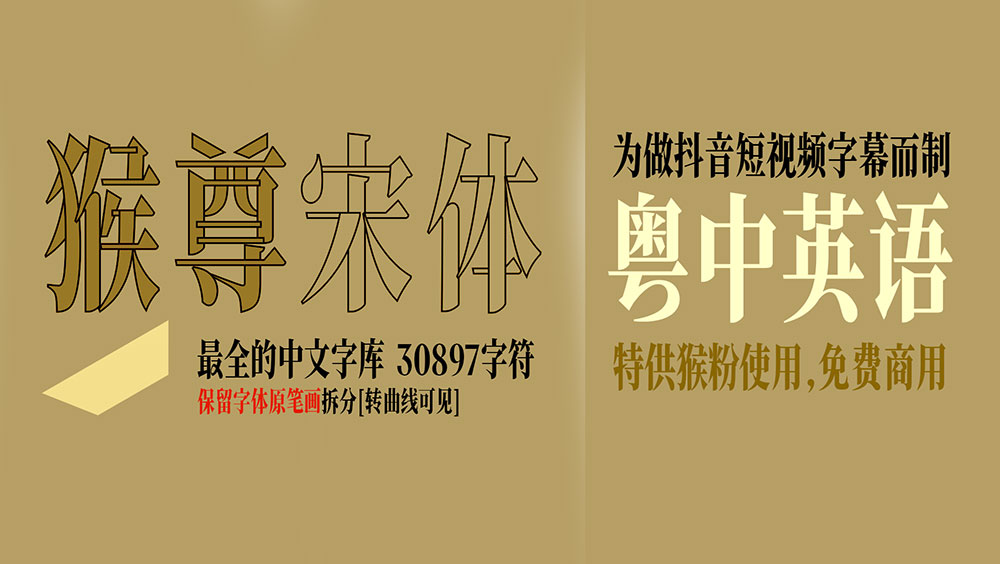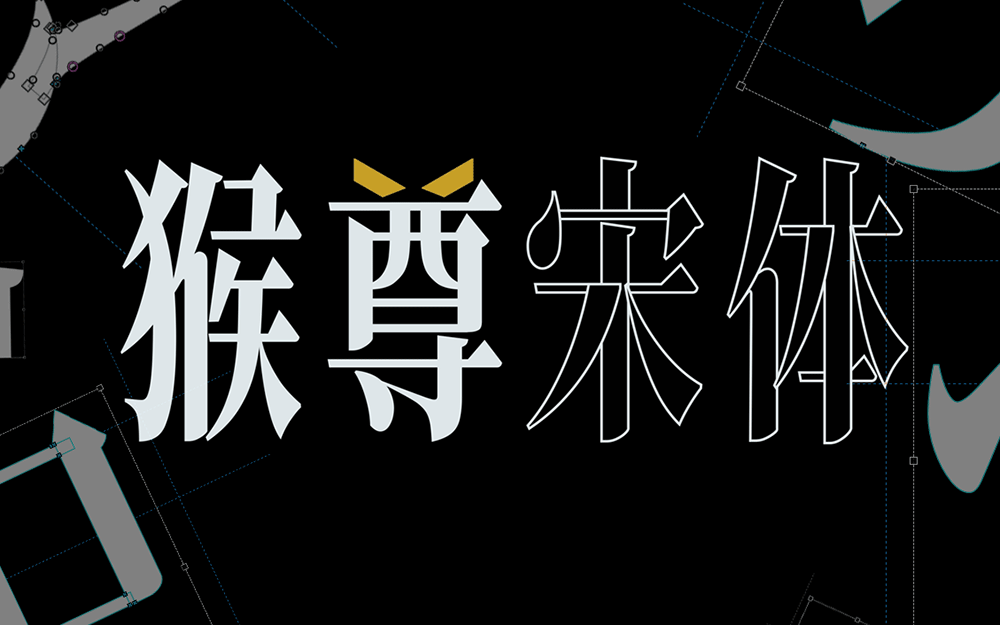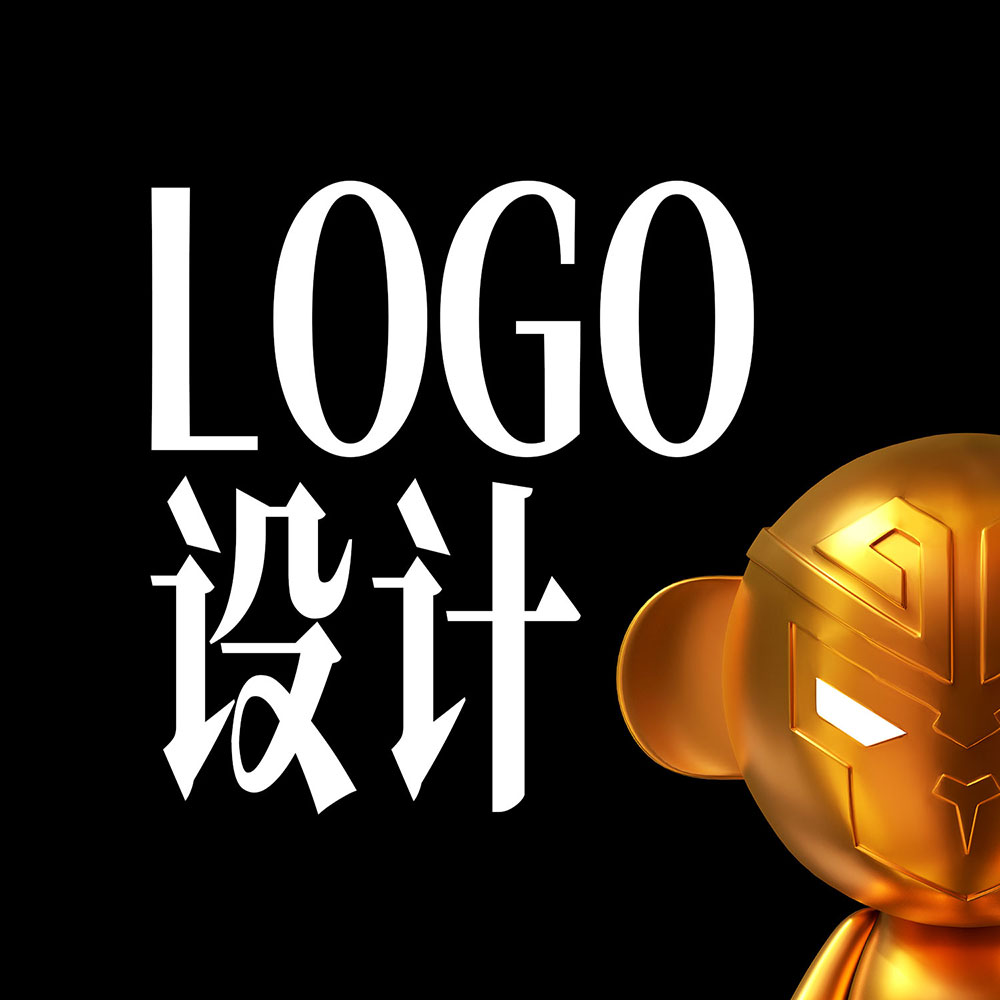
猴尊宋体是由抖音设计博主猴尊于 2023 年基于思源宋体优化而来的一款免费可商用宋体,专为短视频竖屏阅读场景打造。
作者将思源宋体的字形比例调整为黄金比例 (1:1.618),部分笔画融入书法手写感,部分字母、数字和符号等进行了重构设计,并且优化了字间距与行间距,使其在手机竖屏阅读时可以容纳更多文字。所以,猴尊宋体很适合短视频字幕、公众号文章等正文使用场景。当然了,在海报、宣传册、包装设计、品牌标识等大标题场景下也很精致。
| 对比项 | 猴尊宋体 | 思源宋体 |
|---|
| 比例 | 黄金比例优化 | 标准比例 |
| 设计重点 | 短视频竖屏阅读 | 通用场景 |
| 笔画特点 | 加入书法感 | 标准宋体笔画 |
| 字重 | 1 种 | 7 种 (ExtraLight 到 Black) |
| 语言支持 | 简体中文为主 | 简繁日韩四语全面支持 |